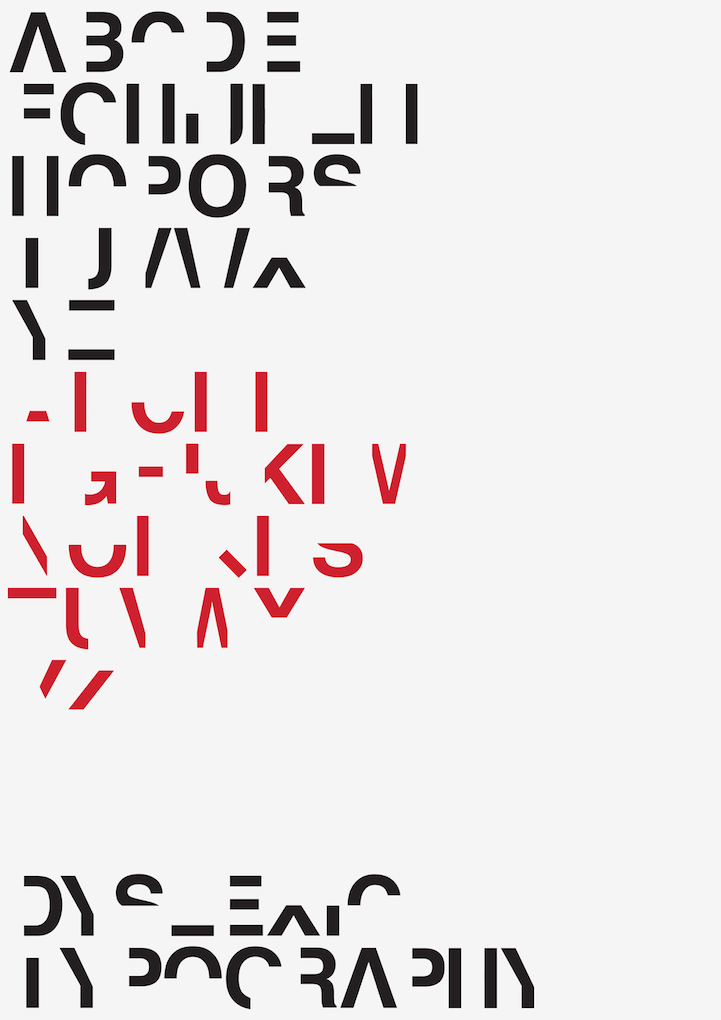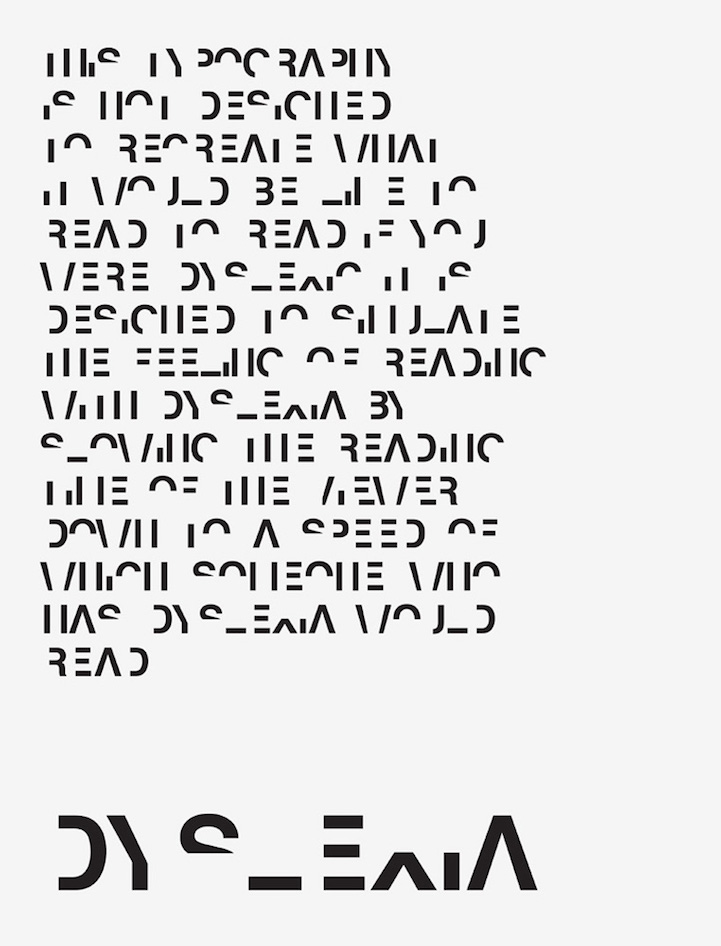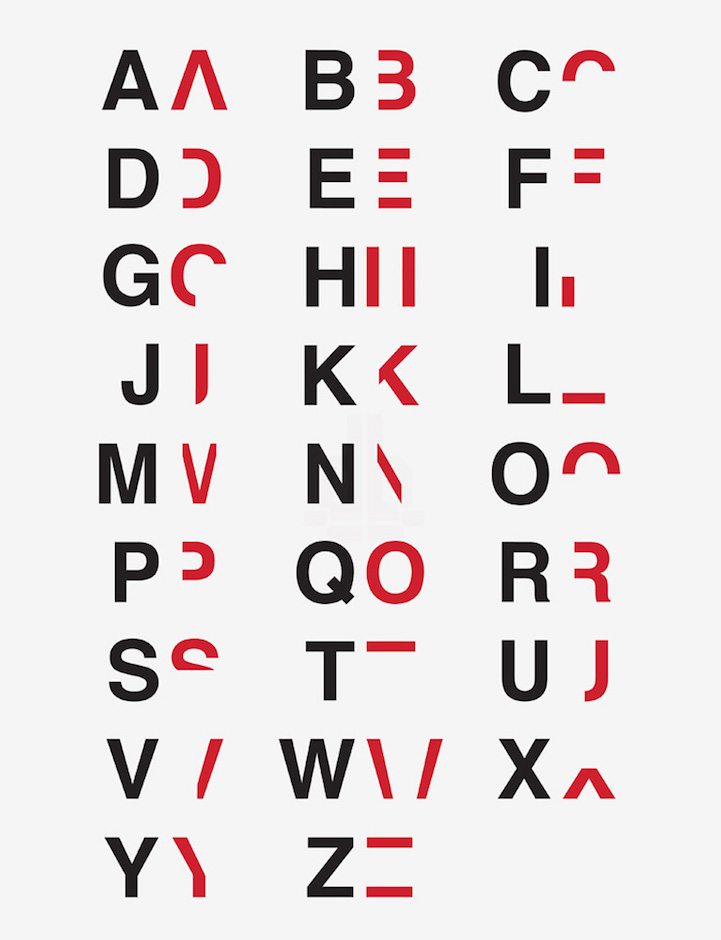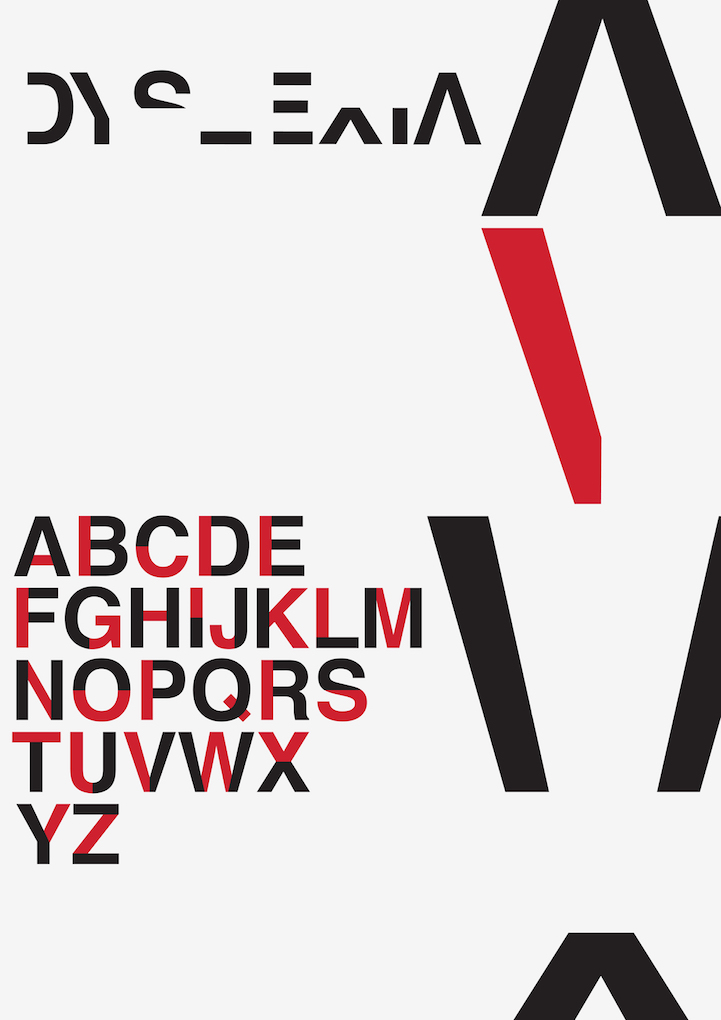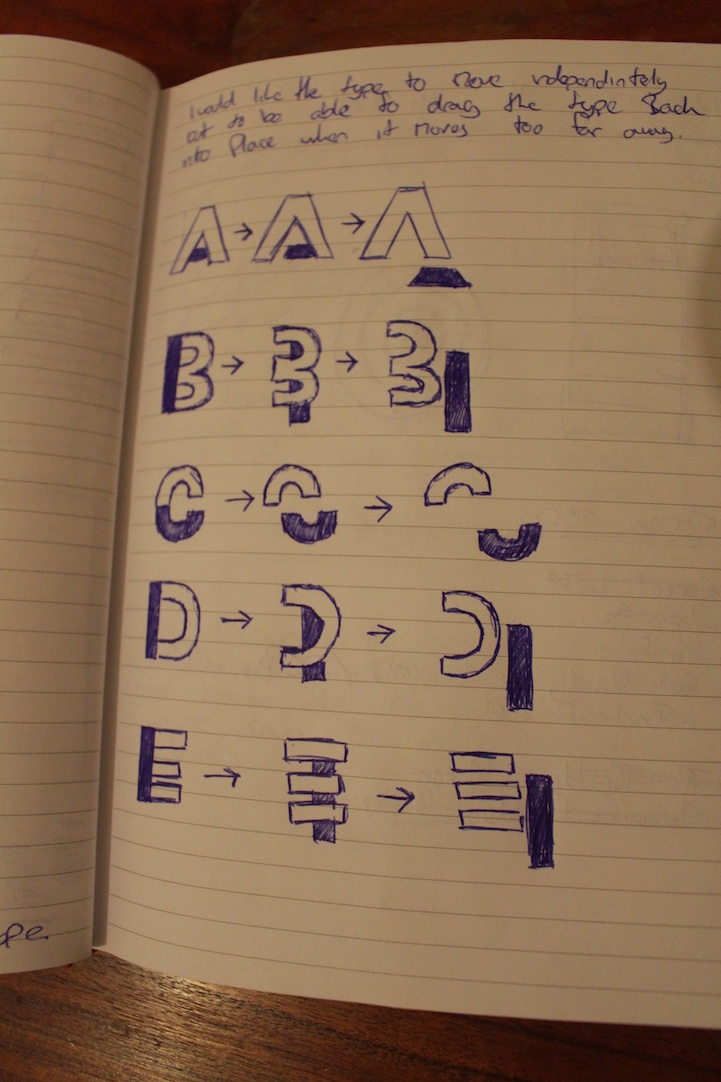
Solo durante il suo ultimo anno come studente alla London School of Communications al designer Daniel Britton è stata diagnosticata la dislessia. Quando ha detto ai suoi compagni di classe e agli insegnanti del suo disturbo, non capivano veramente come si sentiva Daniel. Quindi, usando le sue doti di designer, Britton ha creato un modo per mostrare loro quello che voleva dire. La soluzione è stata creazione di un font chiamato Dislessia.
Il progetto di Britton simula il senso di frustrazione di una persona dislessica quando lui o lei cerca di leggere. Ha usato il font Helvetica come base e ha poi sottratto circa il 40% delle linee del carattere tipografico. Con buona parte di ogni lettera ormai andata, ogni parola è ben più difficile da decifrare.
Il designer sta lavorando per rendere Dislessia un font scaricabile da tutti.